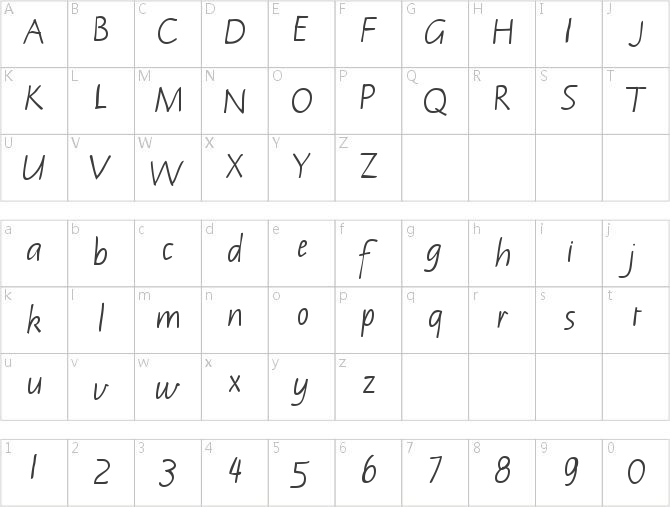
字體名稱(chēng): Notehan
Notehand
Notehand字體字庫(kù)是一款讓人賞心悅目、百看不厭的英文字體,適合各類(lèi)廣告和產(chǎn)品包裝設(shè)計(jì)應(yīng)用,字體大小0.05MB,格式為ttf字體,上傳用戶是星期一,作者/版權(quán)方為未知